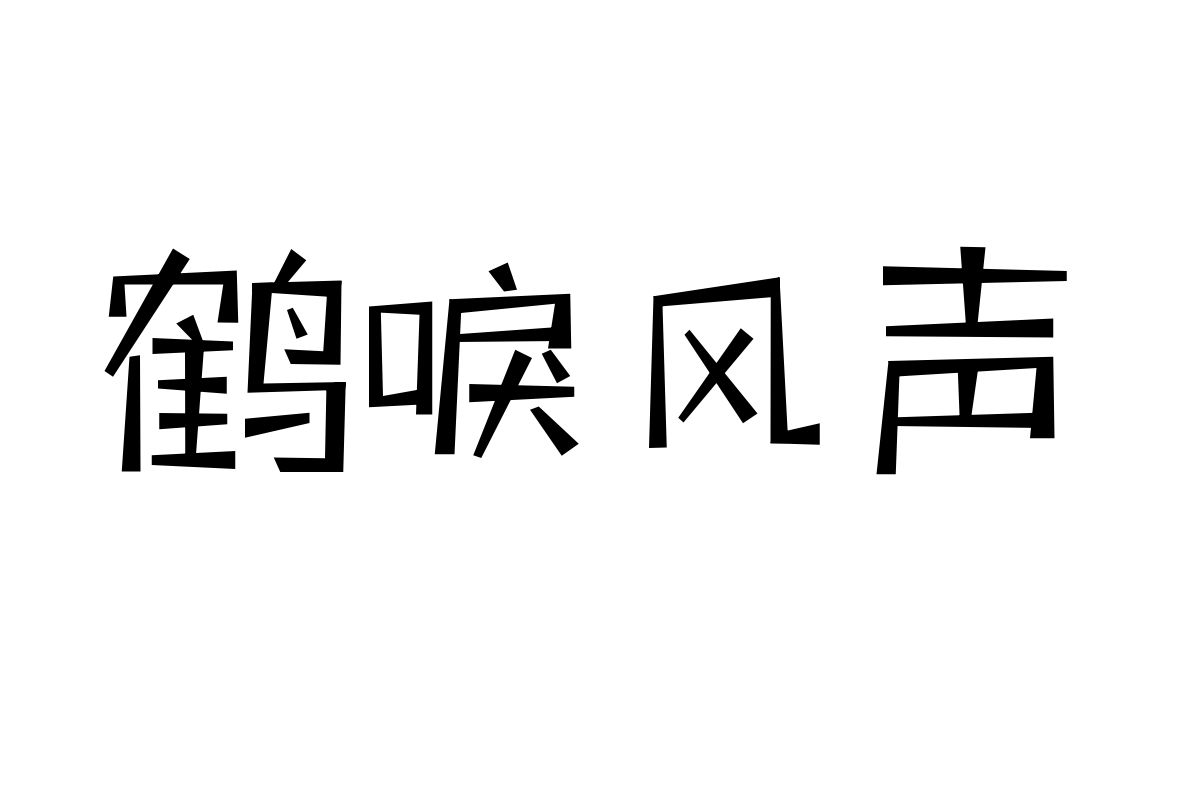
三极玩酷字体是一种现代而独特的无衬线字体,它以其简洁的线条和清晰的轮廓而闻名。这种字体的特点是没有装饰性的元素,因此非常适合用于需要强调清晰性和专业性的场合。
三极玩酷字体的特点包括:
1. 简洁的线条:这种字体的每个字符都由简单的直线组成,没有多余的装饰或曲线。这使得它易于阅读,同时也使得设计更加干净和整洁。
2. 清晰的轮廓:由于其简洁的线条,三极玩酷字体具有非常清晰的轮廓。这使得文字在视觉上更加突出,特别是在背景颜色较暗的情况下。
3. 适合多种场景:无论是在网页设计、广告、标志还是其他任何需要清晰易读的文本的地方,三极玩酷字体都能提供出色的效果。它的简洁性和清晰度使其成为许多设计师的首选。
4. 可定制性:虽然三极玩酷字体本身是无衬线字体,但它仍然可以与其他字体组合使用,以创造出独特的视觉效果。此外,它还支持TrueType字体格式,这意味着你可以根据需要进行自定义和调整。
总的来说,三极玩酷字体是一种功能强大且易于使用的无衬线字体,适用于各种需要清晰易读文本的设计场景。